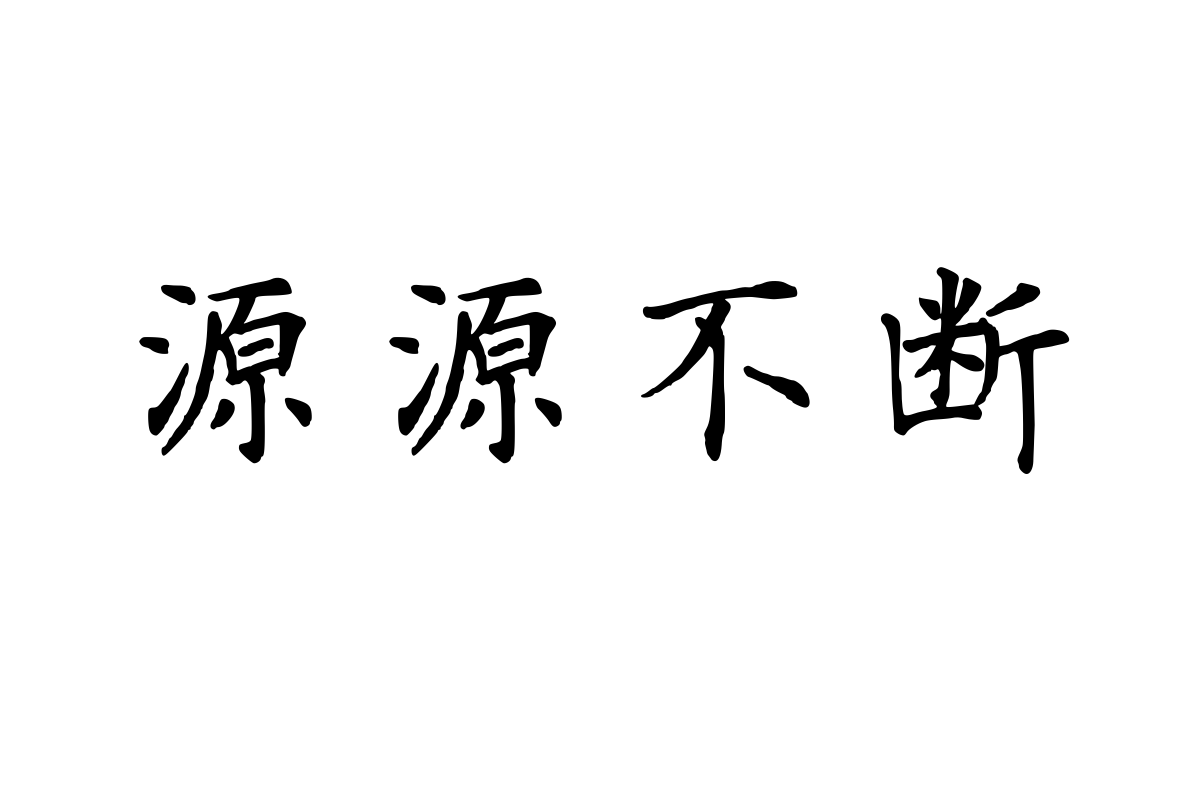
兰米正心楷体是一款具有独特风格的中文字体,其特点是字形端正、笔画流畅,适合用于书写和设计。这款字体的特点包括:
– 字形端正:兰米正心楷体的字形结构严谨,笔画粗细适中,给人一种端庄、稳重的感觉。
– 笔画流畅:兰米正心楷体的笔画连接自然,没有生硬的折线或曲线,使得整体视觉效果更加美观。
– 适用范围广泛:兰米正心楷体适用于各种场合,如书法、印刷、广告等,能够满足不同用户的需求。
总之,兰米正心楷体是一款非常实用的中文字体,无论是在书写还是设计方面都能展现出其独特的魅力。